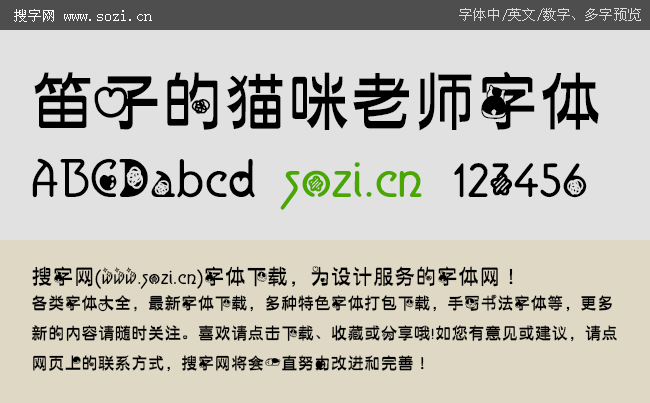
笛子的貓咪老師字體
搜字網(wǎng)給大家提供一款很有趣的手機(jī)中文字體下載。修改者給他起了個(gè)很萌的名字笛子的貓咪老師字體,這款手機(jī)字體在筆畫間插入了有趣的卡通圖案。趣味性實(shí)足,該手機(jī)字體個(gè)性實(shí)足,趣味性強(qiáng),又保持了文字的識(shí)別度,特別適合喜歡手機(jī)字體個(gè)性一些的朋友在手機(jī)上安裝使用。